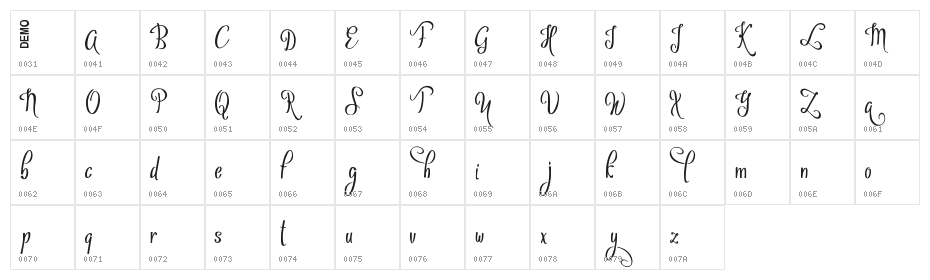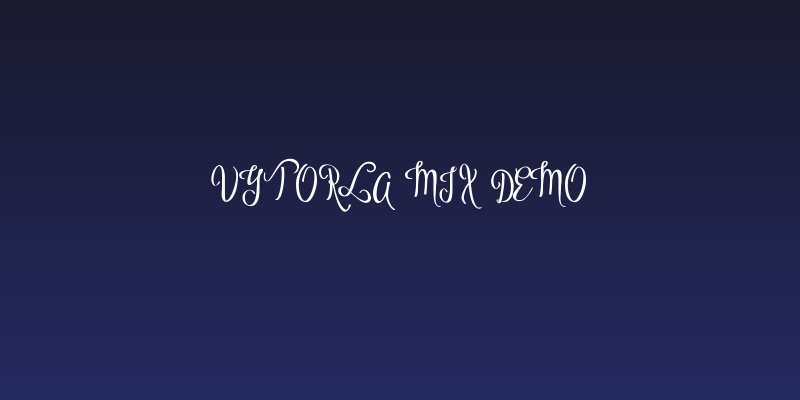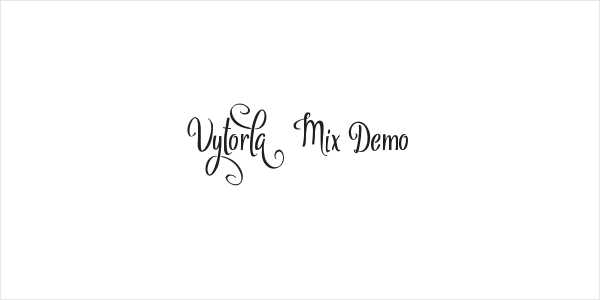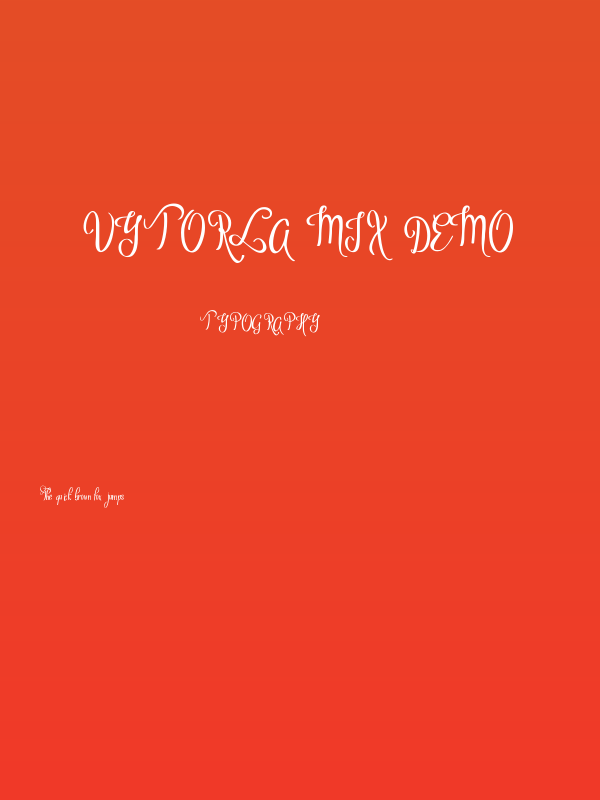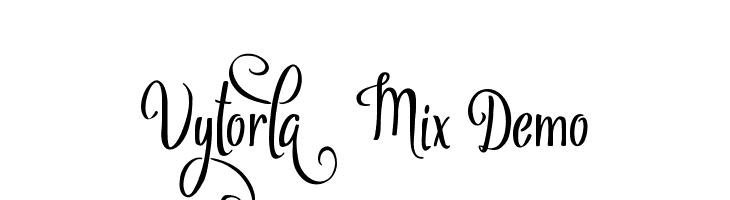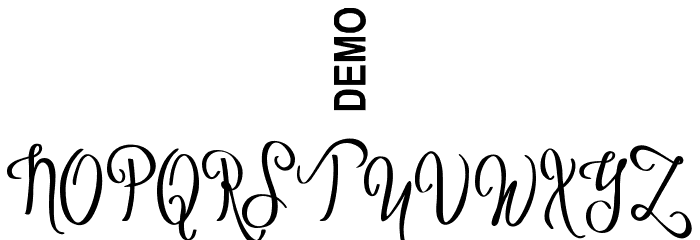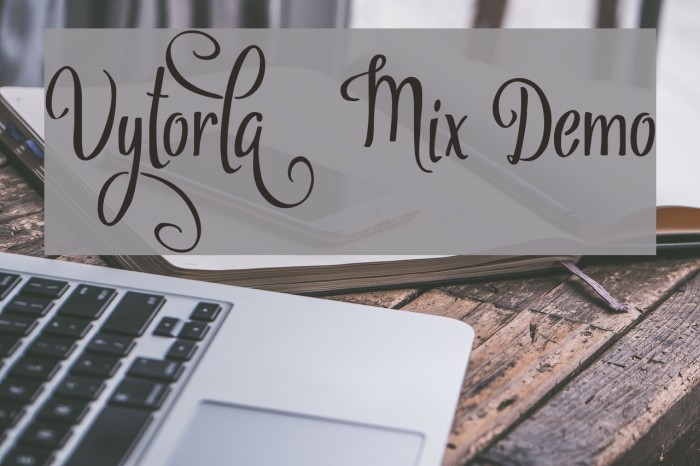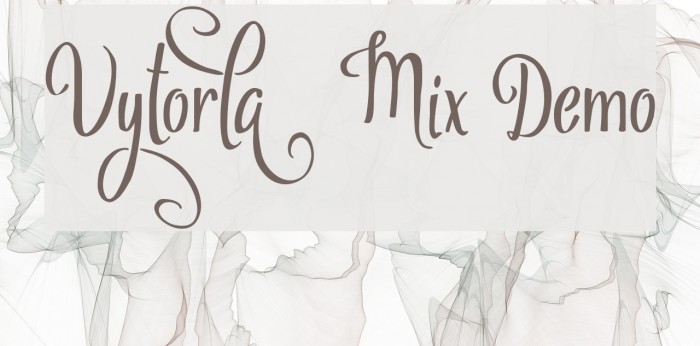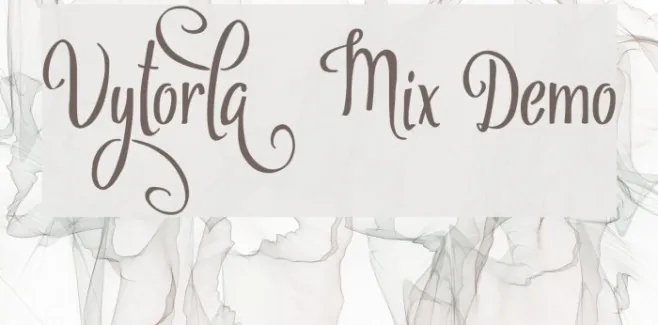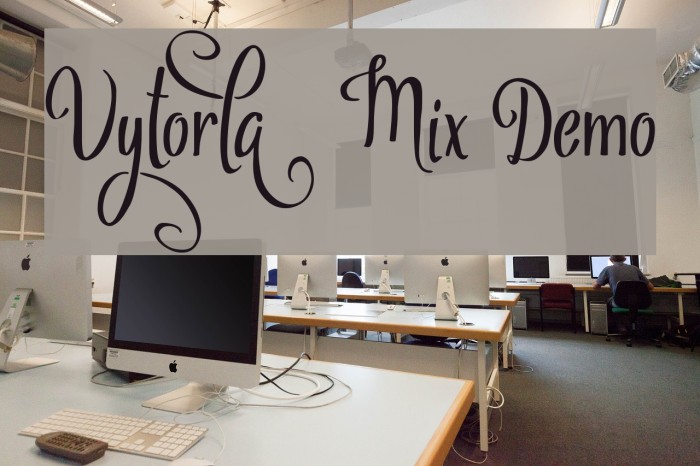
Vytorla Mix Demo Font
| Cas d'utilisation | Logos, Headlines, Invitations |
| Projets proposés | Ideal for wedding invitations, greeting cards, branding, and decorative signage. |